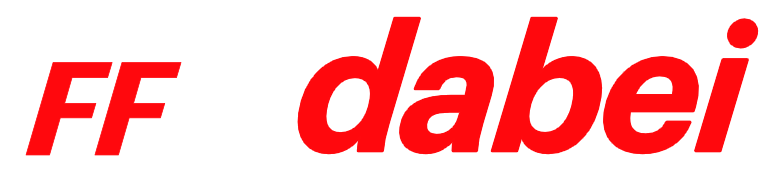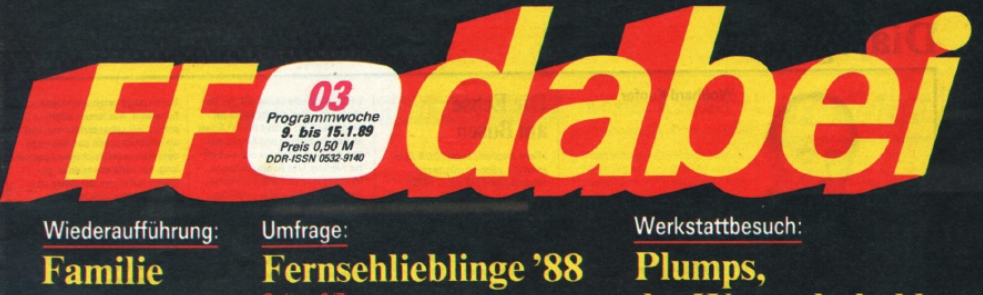
FF dabei Titelschrift (DDR-Programmzeitschrift)
im Berliner Verlag erschien zu DDR-Zeiten die einzige Fernsehillustrierte der DDR.
Die anderen Schriftarten könnten Times (ohne Roman???), Univers sein.
Ich suche die Schrift, welche für den Schriftzug "FF dabei" verwendet wurde.
Alle (mir) bekannten (Folio, Helvetica, ggfs. Maxima) habe ich ausgeschlossen, da der i-Punkt rund ist. Als Orientierung diente mir auch das geschwungene "a" und "d". Kann jemand helfen?
Der i-Punkt sieht mir aufgrund seiner Größe nicht original aus.
Ich habe, außer der Plak, keinen runden i-Punkt gefunden. Ich hatte gedacht, dass es die Maxima ist. Aber auch die "Avus" hat ein anderes kursives a und die mittelfette kursive Variante der Maxima ist nicht käuflich - das gebogene a fiel mir da auf. Da wird es wohl eine manuell gestaltete Variante sein.
Ich habe die Graphik gefunden, bin mir aber nicht sicher, ob es die in der DDR gab.
Im Berliner Verlag gab es in den 80er Jahren Fotosatztechnik und Schriften aus dem Westen. Ich meine, der Verlag war als Parteiverlag der am besten ausgestattetete in der DDR. Ich hab mich da seit Anfang der 80er oft auch bei den Grafikern (einer anderen großen Illustrierten) herumgetrieben und konnte auch selbst mal ein wenig mit diesen Geräten spielen. Wenn man eine Schrift aus dieser Zeit sucht, müßte man sie bei den Fotosatzschriften suchen.
Einen eckigen i-Punkt für eine Titelzeile auszutauschen, wäre auch eine leichte Übung gewesen.
die Graphik ist viel zu neu, denn die DDR wurde bereits 1990 von der Bundesrepublik annektiert und hörtes damit auf zu existieren. Nach meinen Unterlagen erschien die Graphik erst 2009 in freier Wildbahn, war aber wohl schon 2007 existent. Der Eintrag auf Identifont ist etwas verwirrend. Hier meine zsuammengekratzten und leicht ereiterten Daten zur Schrift:
Typeface:    Graphik
Designer:    Christian Schwartz
Year:        2009, 2014, 2017
Publisher:   Commercial Type
Among the typefaces chosen as "Our Favourite Typefaces
of 2007" by the on-line journal Typographica.
Aber wie schon Martin und Ralf angemerkt haben war das möglicherweise eine Einzelanfertigung auf der Basis von damals gängigen Konstruktionsprinzipien, denen die Grafik dann fast 30 Jahren später auch gefolgt ist. Spätestens seit den 1960ern waren Schriften dieser Art schon ziemlich verbreitet und modern. Kann man diese Schrift mit Helvetica und Univers in die Schublade schweizer Typografie stecken?